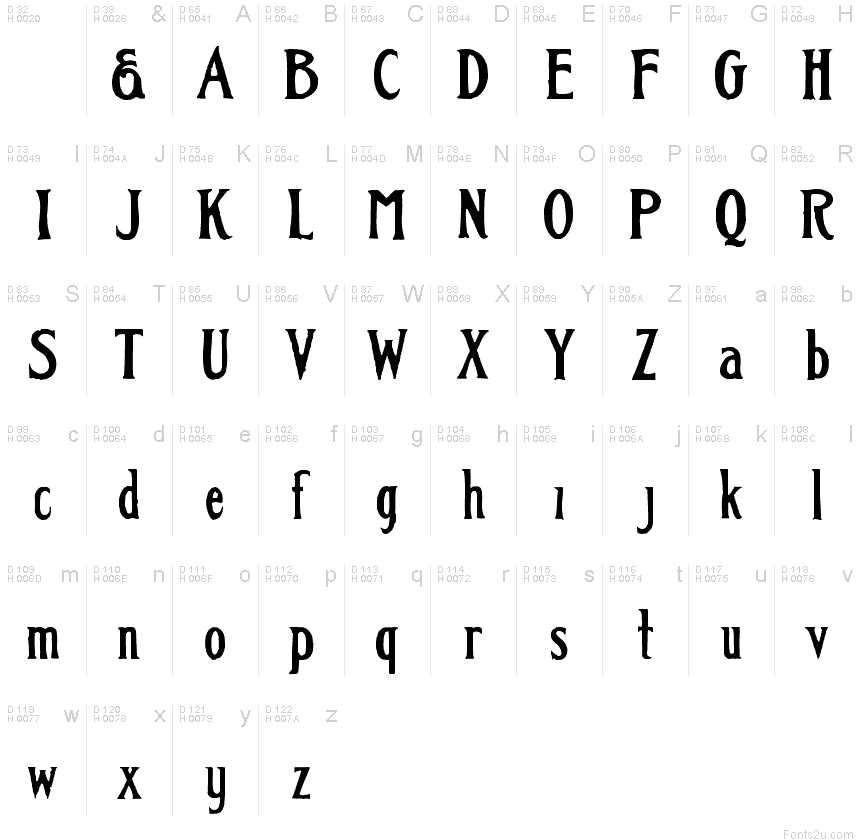
Classic to darmowy, dekoracyjny krój szeryfowy. Ta czcionka przywodzi na myśl dawny, redakcyjny styl „nagłówkowy” – ma wysokie, lekko zwężane litery, wyraziste szeryfy i sprawia wrażenie wyrytej w druku. Ma pewny siebie, tradycyjny rytm, ale nie jest przytłaczająca; wystarczy jedno słowo, by nadać charakter całej kompozycji.
Classic świetnie sprawdzi się na okładkach książek, w tytułach czasopism, logotypach retro, na opakowaniach, szyldach czy plakatach. Ten darmowy krój lubi przestrzeń – używaj go w dużym rozmiarze i dodaj odrobinę światła między literami (tracking), aby szeryfy pozostały ostre. Zestaw go z prostym, bezszeryfowym krojem w tekstach uzupełniających, aby uzyskać wyraźny, czytelny kontrast.